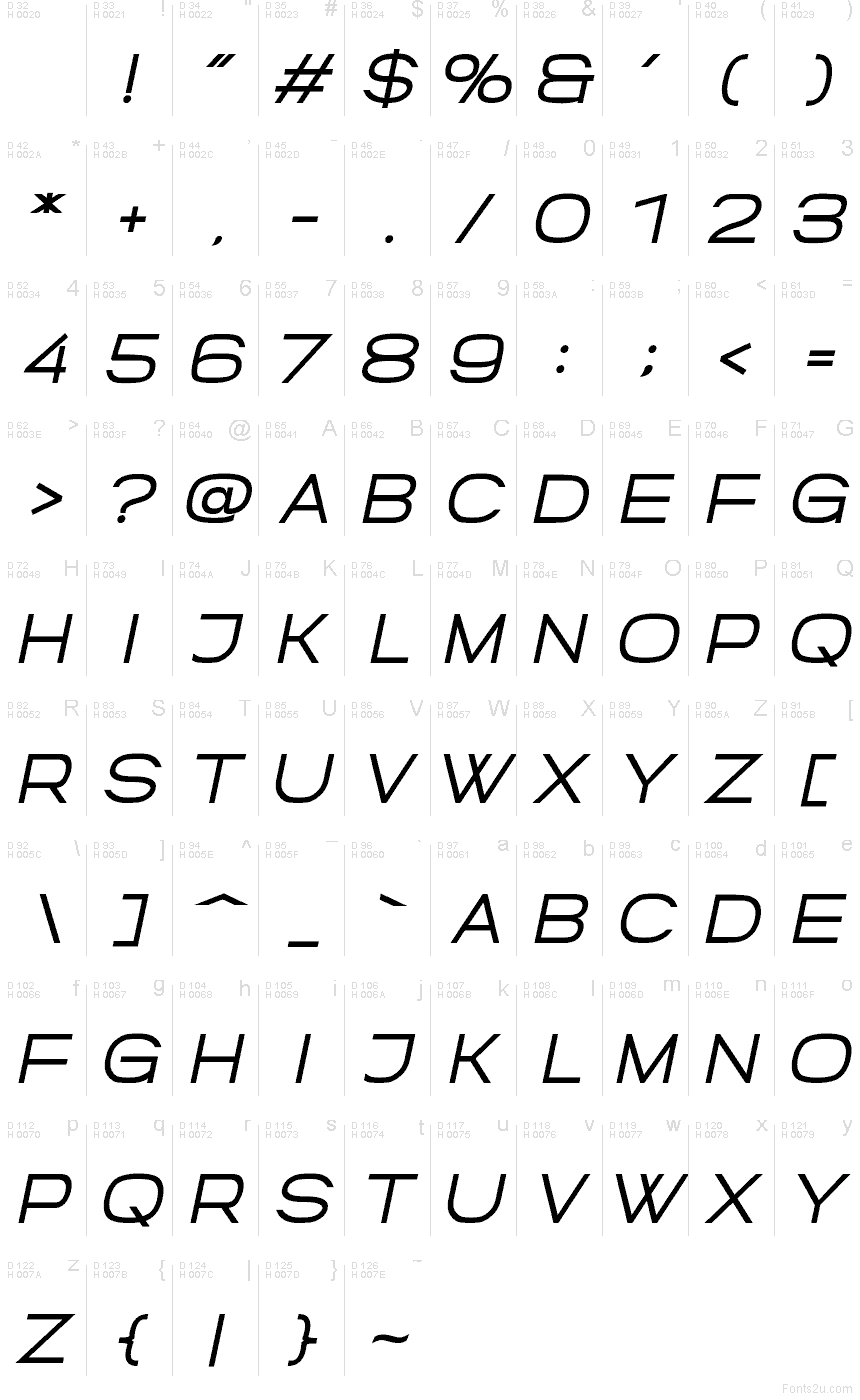
Il font Borndia Bold Italic, creato da Muhamad Fikry Nuralif di Fikryal Studio, è un carattere sans serif corsivo gratuito; Borndia dà l'idea di velocità catturata in un tratto nitido. La sua inclinazione in avanti e le forme larghe e arrotondate lo rendono incisivo senza essere aggressivo, garantendo titoli veloci e fluidi. Il ritmo è serrato e moderno, con un carattere futuristico pronto a scendere in pista.
Borndia Bold Italic brilla nel branding sportivo, nelle etichette per sneaker o streetwear, nei poster tecnologici, nelle miniature per gaming, nei volantini per eventi, nelle pubblicità social d'impatto e nelle scritte sulle confezioni. Usalo in grande formato con una spaziatura generosa per quell'effetto aerodinamico e abbinalo a un sans serif calmo e neutro per il testo principale: questo font gratuito farà il lavoro pesante nei tuoi titoli.